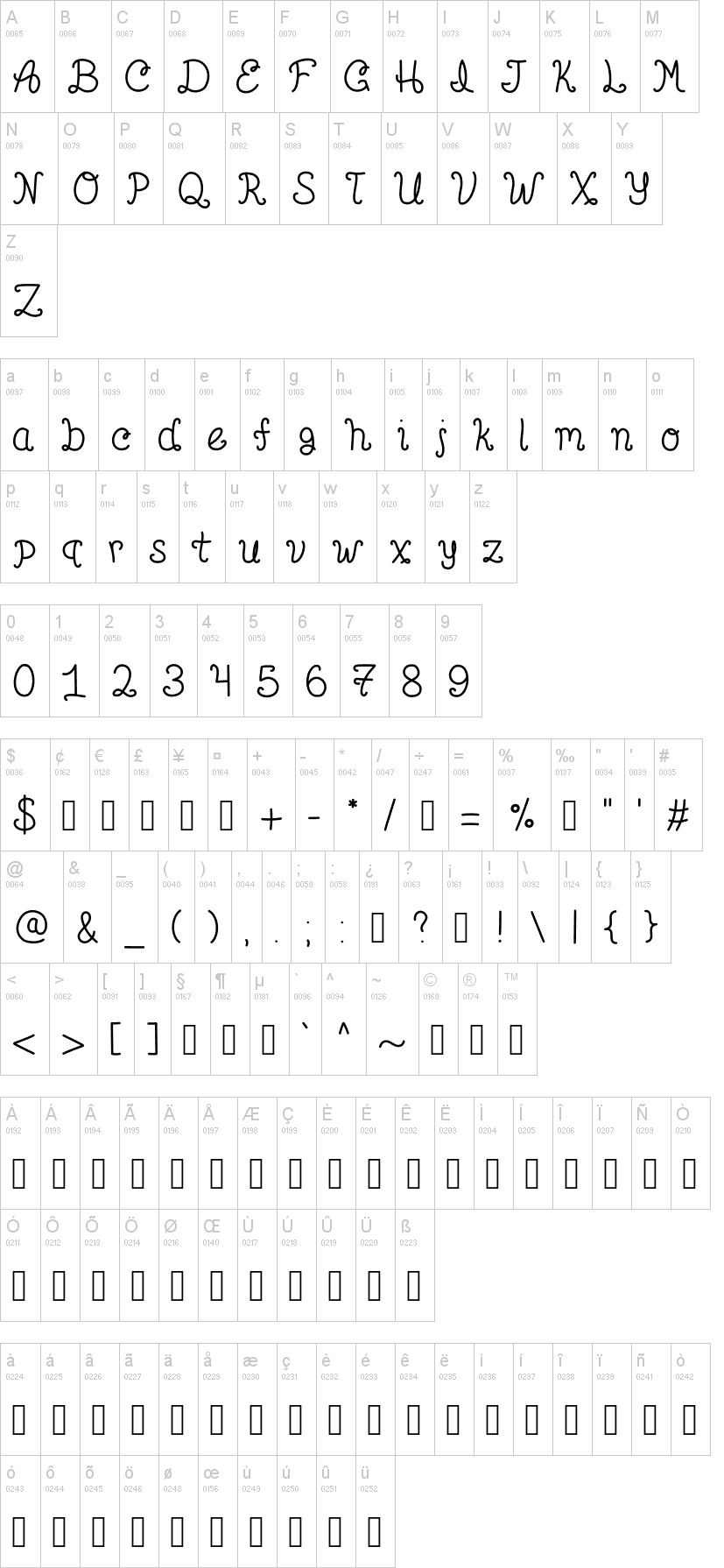
Point Betsie
Point Betsie 是一种优美且简洁的字体,由美国设计师 Matthew Carter 创造。这种字体的灵感来自于底特律的 Point Betsie 码头灯塔,并采用了该灯塔的经典造型和线条设计。 Point Betsie 字体具有优雅的特点,它的线条精细,轮廓线条流畅且匀称。它的字母形状极为简单,没有太多华丽的装饰效果,使得它在大多数情况下都能很好地展现出设计师的意图和文本的清晰度。 Point Betsie 字体是一种非常适合用于印刷和数字媒体设计的字体。它的小写字母和大写字母字体具有一致性和可读性,并且非常适合用于短文段和标题。此外,Point Betsie 字体还拥有多种不同的字重和风格选项,可以满足各种设计需求。
Point Betsie是一款非常不错的手写艺术字体,具有很好的视觉感,适合于文化类的宣传设计、商业类品牌的广告和产品包装设计以及个性化文字排版等较多场景。
Point Betsie字符映射图